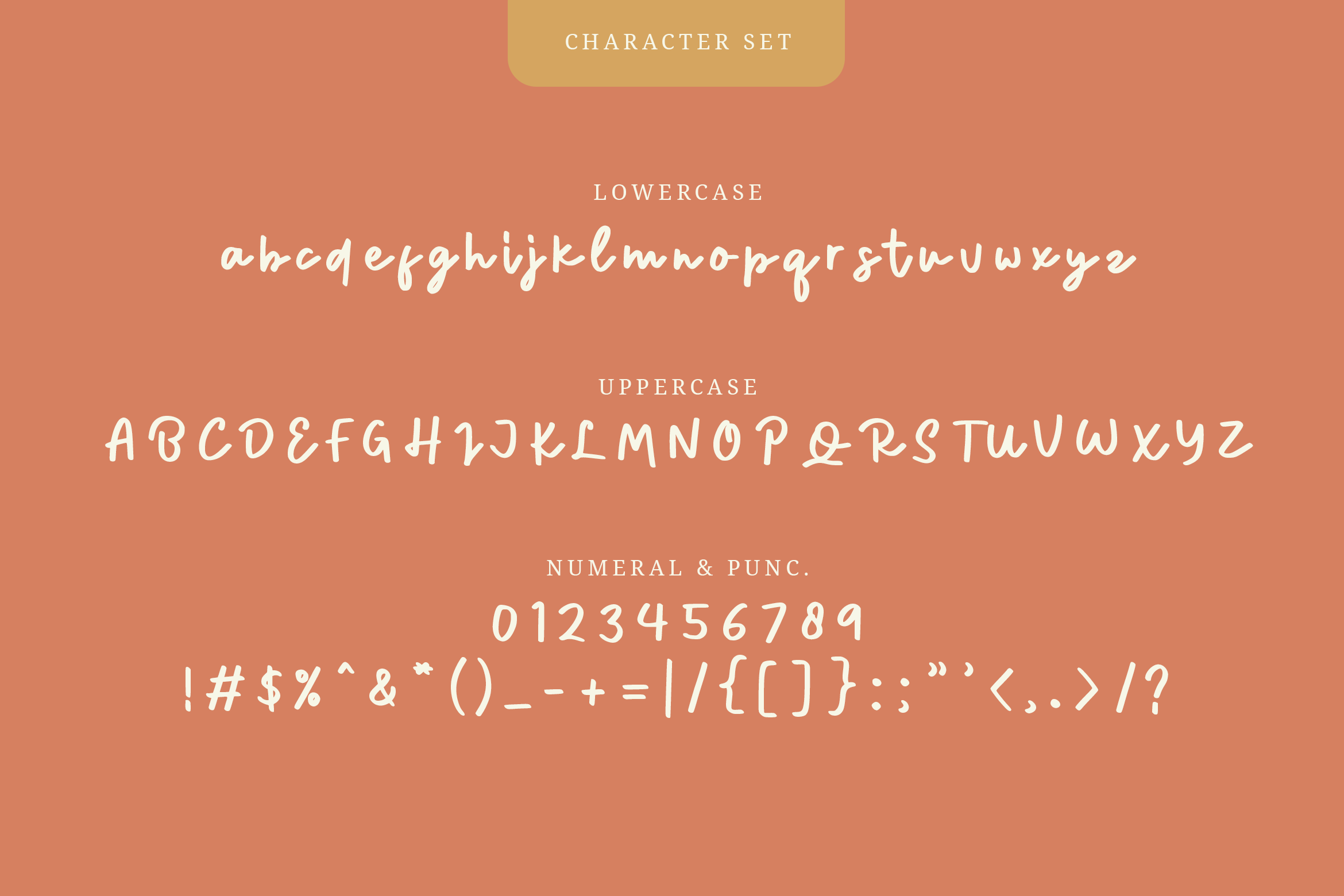
Hatimune是一种独特的书写字体。无论你是否将其用于手工艺、数字设计、演示或贺卡制作,它都是完美的!爱上它令人难以置信的全能风格,并用它来创造壮观的设计!Hatimune是一种独特的书写字体。无论你是否将其用于手工艺、数字设计、演示或贺卡制作,它都是完美的!爱上它令人难以置信的全能风格,并用它来创造壮观的设计!Hatimune是一种独特的书写字体。无论你是否将其用于手工艺、数字设计、演示或贺卡制作,它都是完美的!爱上它令人难以置信的全能风格,并用它来创造壮观的设计!Hatimune是一种独特的书写字体。无论你是否将其用于手工艺、数字设计、演示或贺卡制作,它都是完美的!爱上它令人难以置信的全能风格,并用它来创造壮观的设计!